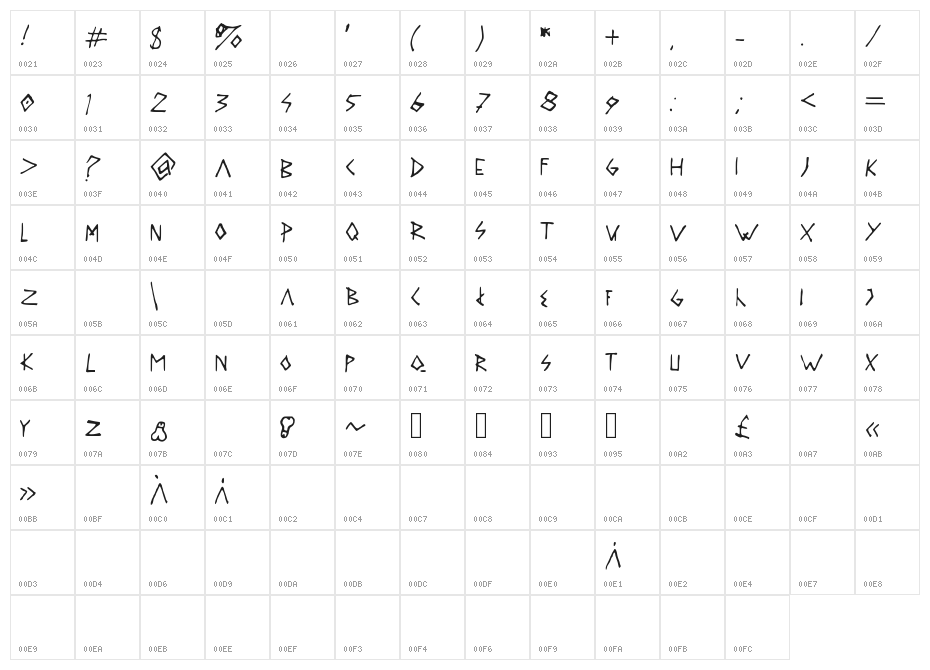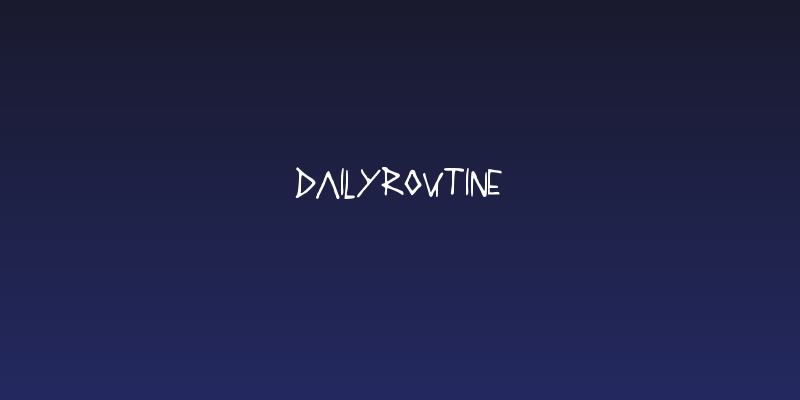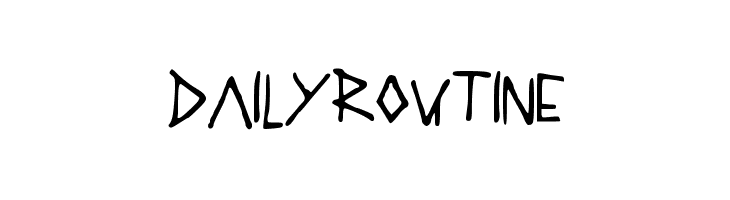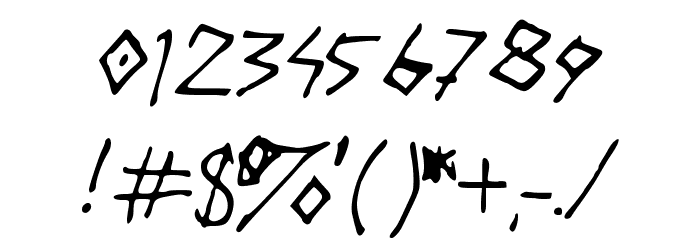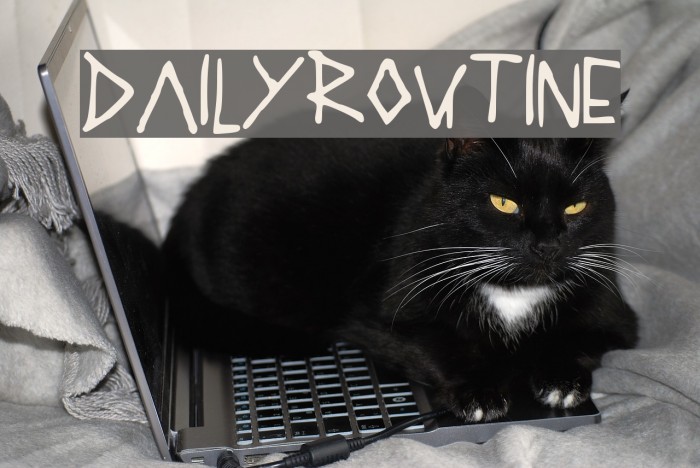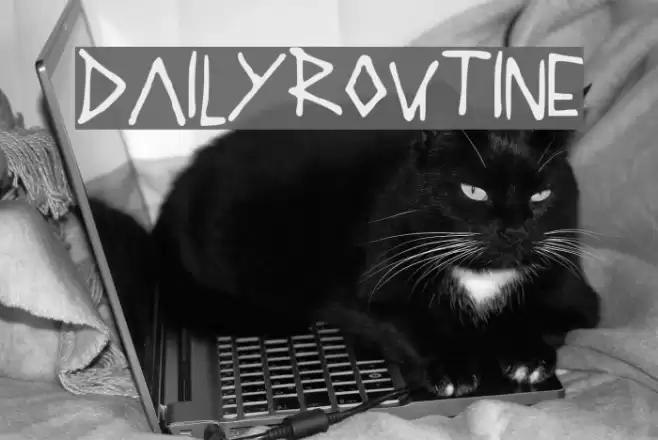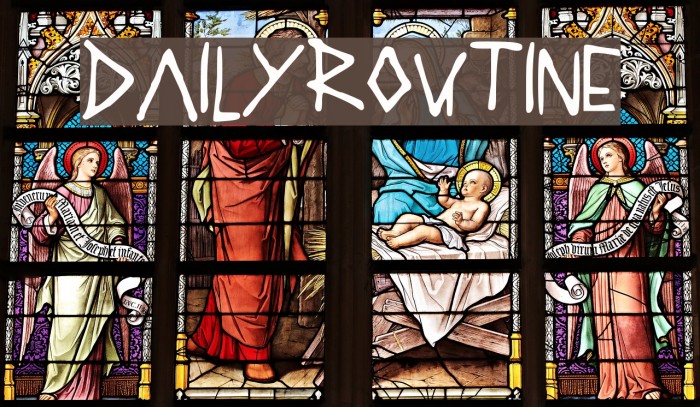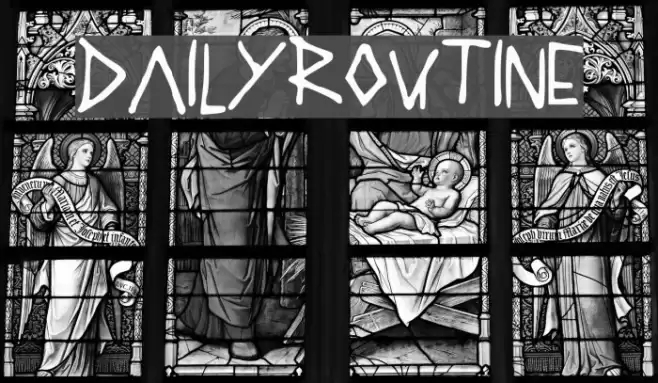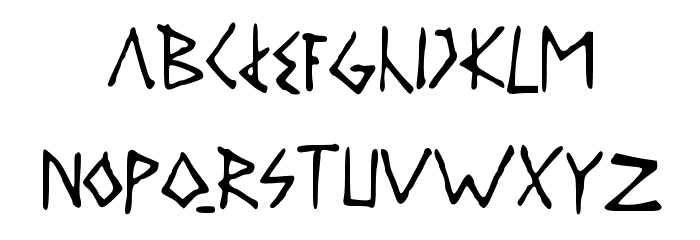
DAILYROUTINE Font
✎ Graffiti
| Категория | Graffiti |
| Область применения | Logos, Headlines, Posters |
| Рекомендуемые проекты | Ideal for creative projects such as posters, album covers, or branding for artistic ventures. It could also be used in digital art, comics, or any design that benefits from a personal, informal touch. |